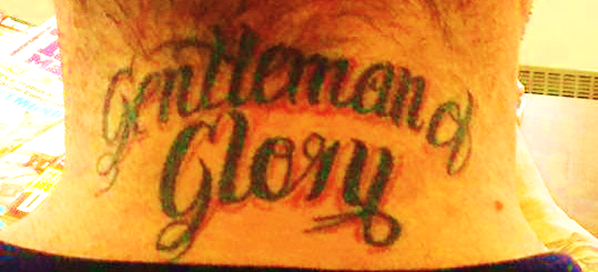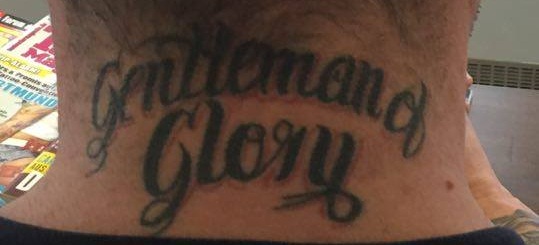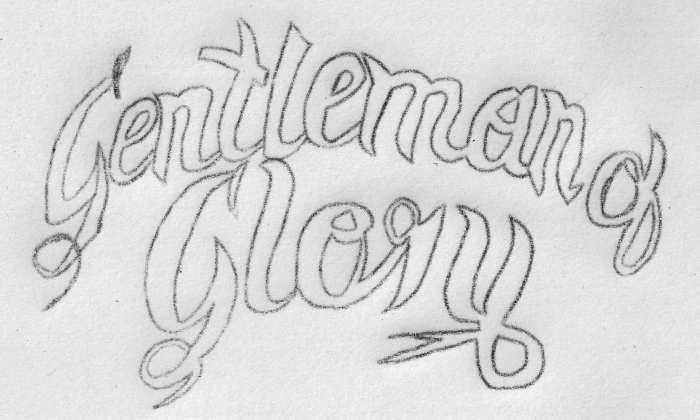
Suche diese Schriftart - speziell die Kontur des "man"of"lory" G natürlich auch :) *verbessertes Bild*
Hallo im letzten Post hatte ich schon eins dieses Bild gepostet.
Ich versuche es einfach nochmal vielleicht sieht man es nun besser.
Habe Diesmal ein verbessertes was man vielleicht deutlicher erkennt oder ersichtlich einiger Konturen ist.
Ein zweites welches darüber abgezeichnet ist.
Mir geht es dringend um diese Schrift Font.
Oder gibt es etwas vergleichbar Ähnliches??
Es geht um ein Familien Portrait was mit dieser Font verdeutlicht werden soll.
Zunächst eine Klärung, es heißt DER Font, aber egal...
Und dann wirst Du einfach keinen Font finden können, der dieser eindeutig auch schon auf dem Entwurf für das Tattoo von Hand geschriebenen Schrifdt sehr deutlich entspricht, dafür sind da einfach Buchstabenformen drin, die keiner, mir bekannten Schrift entsprechen.
Auch sollte man immer dann, wenn Schrift im Bogen, oder in Kurven verkäuft, diese Schrift besser von Hand schreiben, da die Glyphen eines Fonts ja entworfen wurden, um in gerader Linie gesetzt zu werden, und in einen Bogen gezogen oft sehr Verzerrt wirken, bzw. bei einer verbunden geschriebenen Schrift zu fehlerhaften Anschlüssen führen.
Grundsätzlich sind auch gerade für Tattoos hangezeichnete Entwürfe besser geeignet, da hier ja auf einer dreidimensionalen, und noch dazu beweglichen "Unterlage" gesxchrieben wird, und damit so einiges mehr bedacht werden sollte. Generell würde ich bei Schrift mich ohnehin nach einem Spezialisten umsehen, auch wenn dies einen deutlich höheren Preis und eine möglicherweise weite Anreise bedeutet, denn das ist ja schließlich eine Entscheidung, nicht nur für wenige Jahre.